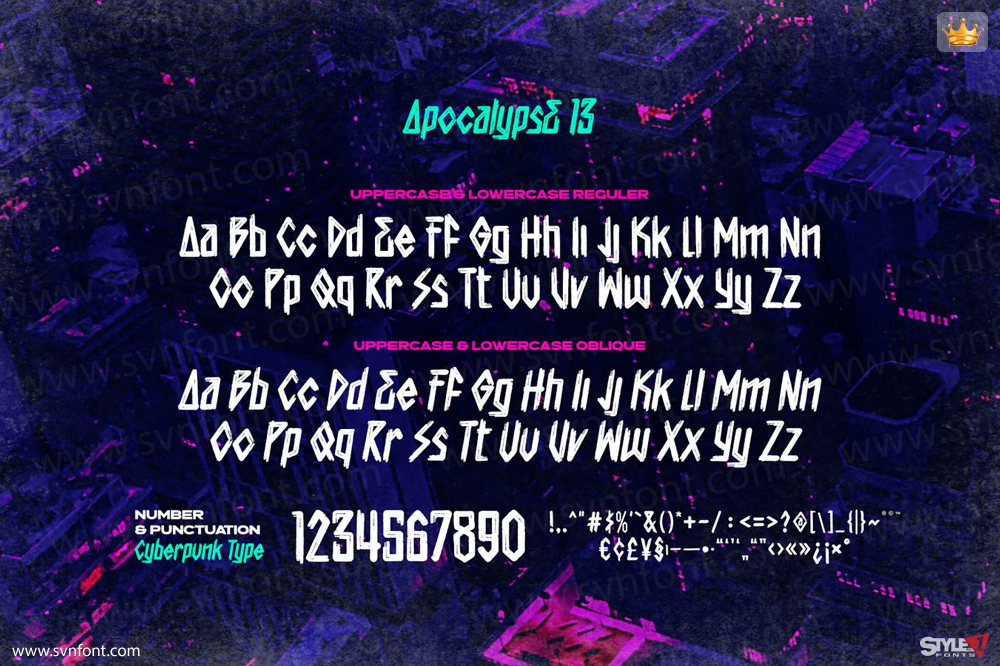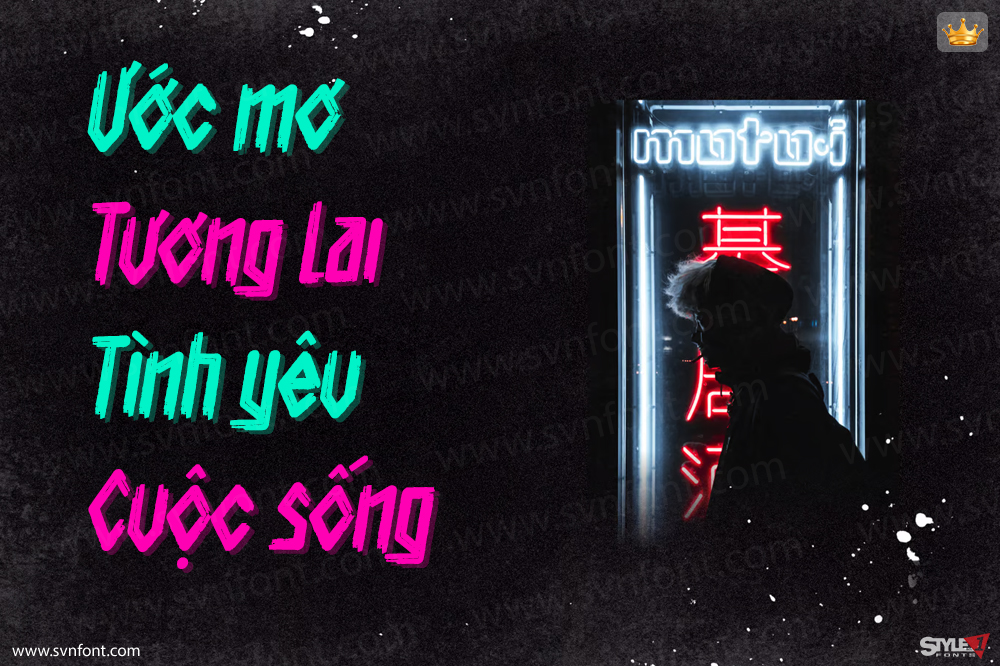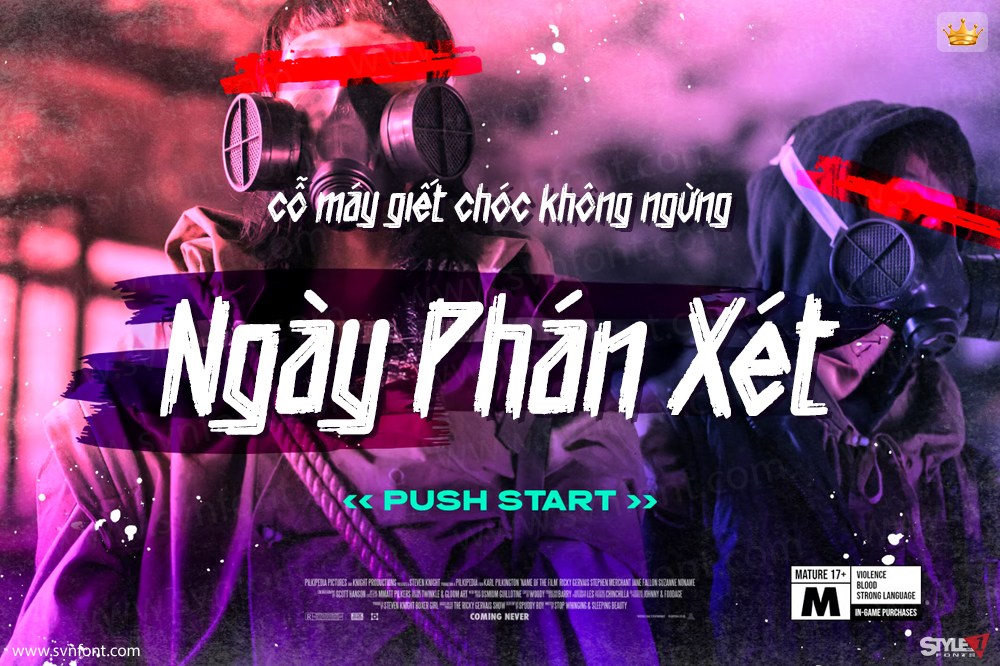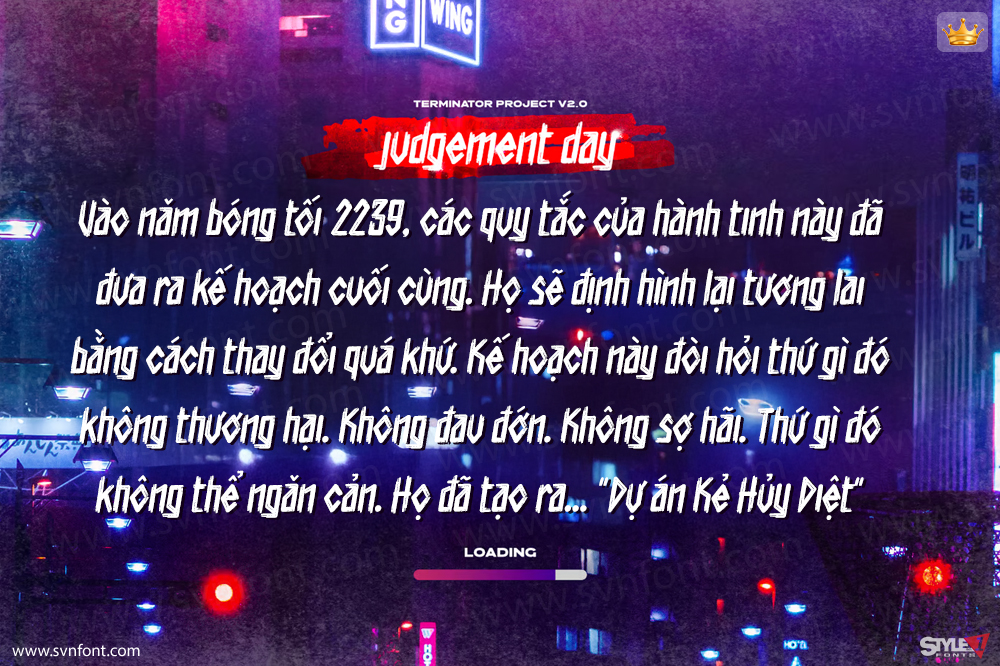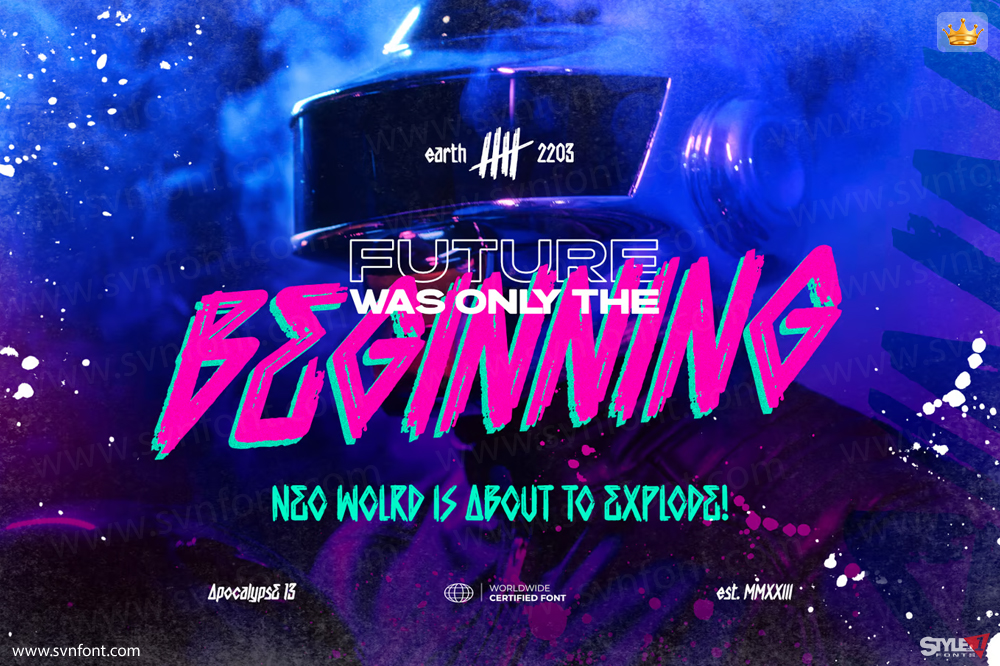
Với thiết kế mạnh mẽ và góc cạnh, kiểu chữ cọ Apocalypse 13 thể hiện một cách hoàn hảo cảm giác về một tương lai đen tối. Kiểu chữ này được tạo ra để đưa bạn đến những con phố tối đen như mực, rực rỡ ánh đèn neon của một đô thị. Nó là sự kết hợp lý tưởng giữa sự mạnh mẽ kỹ thuật và biểu hiện nghệ thuật.
Mỗi ký tự trong Apocalypse 13 được tạo ra một cách tỉ mỉ, sử dụng các cạnh răng cưa và nét cọ mạnh mẽ để gợi lên cảm giác cấp bách và thách thức. Các chữ cái gợi ý một thế giới đang trên bờ vực vô chính phủ bởi vì chúng trông như thể được sơn xịt trên một bức tường bê tông đang sụp đổ.
Kiểu chữ này hoàn hảo cho tiêu đề phim, áp phích phim, tiêu đề trò chơi, logo trò chơi, streamer (người phát trực tiếp), bố cục tạp chí, đồ dùng thời trang, trích dẫn hoặc đơn giản là một lớp phủ văn bản phong cách cho bất kỳ hình ảnh nền nào.